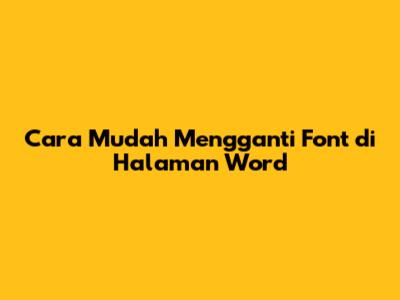
Mengganti font di halaman Word adalah keterampilan dasar yang perlu dikuasai bagi siapa saja yang bekerja dengan Microsoft Word. Baik Anda sedang menulis laporan, membuat resume, atau sekadar membuat surat, pemilihan font yang tepat dapat secara signifikan memengaruhi tampilan dan kesan dokumen Anda. Untungnya, Microsoft Word menawarkan berbagai opsi untuk mengubah font dengan mudah. Mari kita selami cara melakukannya, ya, guys! Prosesnya sebenarnya cukup sederhana, dan setelah Anda menguasainya, Anda akan dapat menyesuaikan tampilan dokumen Anda sesuai keinginan. Jadi, siap untuk menjadi ahli font Word?
Memahami Pentingnya Pemilihan Font
Sebelum kita masuk ke cara mengganti font, penting untuk memahami mengapa pemilihan font itu penting. Pemilihan font bukan hanya masalah estetika; itu juga memengaruhi keterbacaan dan profesionalisme dokumen Anda. Font yang berbeda menyampaikan nada dan gaya yang berbeda. Misalnya, font serif seperti Times New Roman sering dianggap lebih tradisional dan formal, cocok untuk dokumen akademis atau laporan bisnis. Di sisi lain, font sans-serif seperti Arial atau Calibri cenderung lebih modern dan bersih, ideal untuk presentasi atau dokumen yang berorientasi pada tampilan. Nah, guys, pemilihan font yang tepat juga dapat meningkatkan keterbacaan, terutama untuk audiens yang lebih tua atau mereka yang memiliki masalah penglihatan. Font yang mudah dibaca memastikan pesan Anda tersampaikan dengan jelas. Selain itu, konsistensi dalam penggunaan font sangat penting. Gunakan satu font utama untuk badan teks dan satu font lain (atau variasi dari font utama) untuk judul dan subjudul. Hal ini menciptakan tampilan yang kohesif dan profesional. Dengan memilih font yang tepat, Anda dapat memastikan bahwa dokumen Anda terlihat profesional, mudah dibaca, dan sesuai dengan tujuan Anda. Jadi, pikirkan baik-baik sebelum memilih font, ya.
Memilih Font yang Tepat untuk Dokumen Anda
Memilih font yang tepat bisa jadi sedikit membingungkan, tetapi dengan beberapa panduan, Anda bisa melakukannya dengan mudah. Pertama, pertimbangkan tujuan dokumen Anda. Apakah itu laporan bisnis, resume, atau undangan pesta? Setiap jenis dokumen memiliki kebutuhan font yang berbeda. Kedua, perhatikan audiens Anda. Siapa yang akan membaca dokumen Anda? Jika Anda menulis untuk audiens yang lebih tua, pilih font yang mudah dibaca, seperti Times New Roman atau Georgia. Ketiga, pikirkan tentang gaya yang ingin Anda sampaikan. Apakah Anda ingin terlihat formal, kasual, atau kreatif? Font serif seperti Garamond atau Baskerville seringkali menyampaikan kesan formal, sementara font sans-serif seperti Helvetica atau Open Sans cenderung lebih kasual. Keempat, perhatikan keterbacaan. Pastikan font yang Anda pilih mudah dibaca, baik dalam ukuran kecil maupun besar. Hindari font yang terlalu rumit atau dekoratif untuk badan teks. Terakhir, eksperimen! Cobalah berbagai font untuk melihat mana yang paling cocok dengan dokumen Anda. Microsoft Word menyediakan pratinjau langsung, yang memungkinkan Anda melihat bagaimana font yang berbeda akan terlihat sebelum Anda memilihnya. Ingat, guys, tidak ada jawaban yang benar atau salah dalam pemilihan font. Yang penting adalah memilih font yang sesuai dengan tujuan, audiens, dan gaya dokumen Anda.
Langkah-Langkah Mengganti Font di Word
Oke, sekarang kita masuk ke bagian yang paling penting: cara mengganti font di Word. Prosesnya cukup mudah, dan Anda dapat melakukannya dalam beberapa langkah sederhana. Pertama, buka dokumen Word Anda. Pastikan dokumen yang ingin Anda edit sudah terbuka di Microsoft Word. Kedua, pilih teks yang ingin Anda ubah font-nya. Anda dapat memilih seluruh dokumen dengan menekan Ctrl + A (atau Cmd + A di Mac), atau Anda dapat memilih bagian tertentu dengan mengklik dan menyeret kursor Anda di atas teks yang ingin Anda ubah. Ketiga, buka menu font. Di tab “Beranda” (Home) di pita (ribbon), Anda akan melihat bagian “Font”. Di sini, Anda dapat menemukan semua opsi yang Anda butuhkan untuk mengubah font. Keempat, pilih font yang Anda inginkan. Klik pada menu drop-down font, yang biasanya menampilkan nama font saat ini (misalnya, “Calibri”). Daftar semua font yang tersedia akan muncul. Gulir ke bawah atau ketik nama font yang Anda inginkan di kotak pencarian untuk menemukannya. Klik pada nama font untuk memilihnya. Kelima, sesuaikan ukuran dan gaya font. Di bagian “Font”, Anda juga dapat mengubah ukuran font (menggunakan menu drop-down ukuran font atau tombol “A” besar dan kecil) dan gaya font (seperti tebal, miring, atau bergaris bawah). Keenam, ulangi langkah-langkah ini untuk bagian lain dari dokumen Anda. Anda dapat mengulangi proses ini untuk mengubah font bagian lain dari dokumen Anda, seperti judul, subjudul, atau paragraf tertentu. Mudah, kan, guys?
Mengubah Font Default untuk Dokumen Baru
Jika Anda ingin font yang Anda pilih menjadi default untuk semua dokumen baru yang Anda buat, Anda bisa melakukannya dengan mudah, lho! Ini akan menghemat waktu Anda karena Anda tidak perlu mengubah font setiap kali Anda membuat dokumen baru. Pertama, buka dokumen Word baru. Atau, jika Anda sudah membuka dokumen, pastikan tidak ada teks yang dipilih. Kedua, ubah font sesuai keinginan Anda. Ikuti langkah-langkah yang dijelaskan di atas untuk memilih font, ukuran, dan gaya yang Anda inginkan. Ketiga, klik kanan di area kosong dokumen. Ini akan menampilkan menu konteks. Keempat, pilih “Font…” dari menu konteks. Ini akan membuka kotak dialog “Font”. Kelima, klik tombol “Default…” di sudut kiri bawah kotak dialog. Ini akan membuka kotak dialog konfirmasi. Keenam, pilih opsi untuk mengatur font sebagai default untuk dokumen ini saja atau untuk semua dokumen berdasarkan template Normal.dotm (atau template default lainnya). Ketujuh, klik “OK”. Word akan menyimpan pengaturan font sebagai default untuk dokumen baru Anda. Sekarang, setiap kali Anda membuat dokumen baru, font yang Anda pilih akan menjadi font default. Selamat, guys! Anda sekarang dapat mengatur font default Anda sendiri.
Tips Tambahan dan Fitur Lanjutan
Selain cara mengganti font dasar, ada beberapa tips tambahan dan fitur lanjutan yang dapat membantu Anda menyesuaikan tampilan dokumen Anda. Pertama, gunakan gaya (styles). Gaya adalah cara yang hebat untuk mengelola format dalam dokumen Anda secara konsisten. Anda dapat membuat gaya untuk judul, subjudul, badan teks, dan elemen lainnya, yang memungkinkan Anda mengubah font dan format lainnya dengan mudah di seluruh dokumen. Kedua, gunakan format painter. Fitur ini memungkinkan Anda menyalin format dari satu teks ke teks lainnya. Cukup pilih teks yang diformat dengan benar, klik ikon “Format Painter” di tab “Beranda”, dan kemudian klik pada teks yang ingin Anda format. Ketiga, gunakan fitur “Temukan dan Ganti”. Fitur ini sangat berguna untuk mengganti font di seluruh dokumen. Cukup buka fitur “Temukan dan Ganti” (Ctrl + H), masukkan font lama di kolom “Temukan” dan font baru di kolom “Ganti dengan”, lalu klik “Ganti Semua”. Keempat, pertimbangkan untuk menggunakan font yang tertanam (embedded fonts). Jika Anda berbagi dokumen dengan orang lain, Anda dapat menyematkan font untuk memastikan bahwa mereka melihat font yang sama seperti yang Anda lihat. Untuk melakukan ini, buka “Opsi” (File > Opsi), pilih “Simpan”, dan centang kotak “Sematkan font dalam file”. Kelima, jelajahi berbagai font. Microsoft Word menawarkan berbagai macam font, baik yang sudah terinstal maupun yang dapat Anda unduh dari internet. Luangkan waktu untuk menjelajahi berbagai font untuk menemukan font yang paling sesuai dengan kebutuhan Anda. Jangan takut untuk bereksperimen, ya, guys!
Mengatasi Masalah Umum Saat Mengganti Font
Kadang-kadang, Anda mungkin menghadapi beberapa masalah saat mengganti font di Word. Jangan khawatir, ini cukup umum, dan ada solusi untuk sebagian besar masalah tersebut. Pertama, font tidak muncul dalam daftar. Jika font yang Anda inginkan tidak muncul dalam daftar, pastikan font tersebut sudah terinstal di komputer Anda. Jika belum, Anda perlu menginstal font tersebut terlebih dahulu. Kedua, font terlihat berbeda di komputer lain. Ini mungkin terjadi jika orang lain tidak memiliki font yang sama yang terinstal di komputer mereka. Untuk mengatasi masalah ini, sematkan font dalam dokumen Anda (seperti yang dijelaskan di atas). Ketiga, font berubah secara tiba-tiba. Ini mungkin terjadi jika Anda menggunakan gaya yang tidak dikonfigurasi dengan benar. Periksa gaya yang Anda gunakan dan pastikan bahwa mereka dikonfigurasi dengan font yang Anda inginkan. Keempat, teks menjadi tidak terbaca. Jika font yang Anda pilih terlalu kecil atau terlalu rumit, teks mungkin menjadi sulit dibaca. Ubah ukuran font atau pilih font yang lebih mudah dibaca. Kelima, masalah kompatibilitas. Pastikan Anda menggunakan versi Microsoft Word yang kompatibel dengan font yang Anda gunakan. Beberapa font mungkin tidak berfungsi dengan baik di versi Word yang lebih lama. Jika Anda menghadapi masalah apa pun saat mengganti font, jangan ragu untuk mencari bantuan online atau bertanya kepada teman atau kolega Anda. Ingat, guys, selalu ada solusi untuk setiap masalah.
Kesimpulan: Kuasai Seni Mengganti Font!
Mengganti font di halaman Word adalah keterampilan penting yang akan sangat berguna bagi Anda dalam berbagai situasi. Dengan memahami pentingnya pemilihan font, mengikuti langkah-langkah sederhana untuk mengubah font, dan memanfaatkan tips serta fitur lanjutan, Anda dapat membuat dokumen yang terlihat profesional, mudah dibaca, dan sesuai dengan tujuan Anda. Jangan ragu untuk bereksperimen dengan berbagai font, ukuran, dan gaya untuk menemukan kombinasi yang paling cocok untuk Anda. Ingat, guys, latihan membuat sempurna. Semakin banyak Anda berlatih, semakin mahir Anda dalam menguasai seni mengganti font di Word. Jadi, teruslah mencoba, berkreasi, dan jadikan dokumen Anda lebih menarik dan profesional! Selamat mencoba, dan semoga sukses!